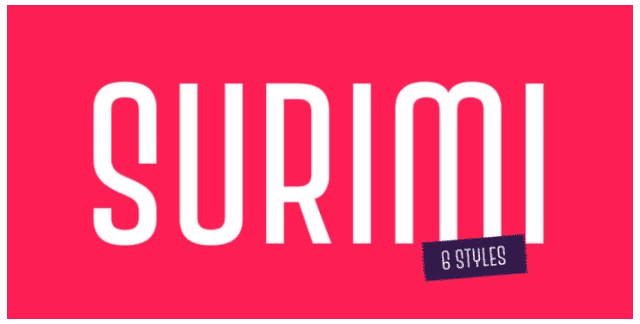
Surimi - это конденсированный шрифт, представленный в шести стилях.
Созданный для того, чтобы выделяться своими низкими поперечными полосами и чередованием букв в одном регистре, этот маленький классный семейный шрифт отлично подходит для создания заголовков и логотипов.
Шрифт включает диакритические знаки для западноевропейских языков, табличные и пропорциональные фигуры, а также 4 стилистических набора: